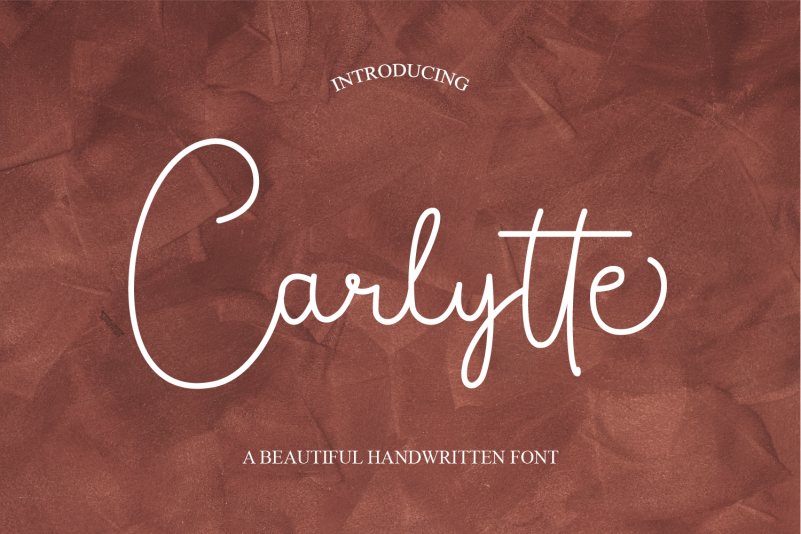
Carlytte Font – Fonte Grátis
Carlytte Font
A Carlytte Font é uma elegante seleção de letra à mão que oferece um toque fino e atraente. Seu design distintivo e suas letras bem redondas fazem dela algo extraordinariamente versátil, capaz de transformar qualquer projeto em algo surpreendentemente único e incrivelmente bonito. Não se limite às possibilidades da Carlytte Font – ela é tão versátil quanto sua natureza delicada permite. Engane-se no entusiasmo pela capacidade deslumbrante dela para criar designs espectaculares, e venha explorar a fonte Carlytte, uma obra-prima à mão que fará seu trabalho de design florescer em novas formas e estilos.